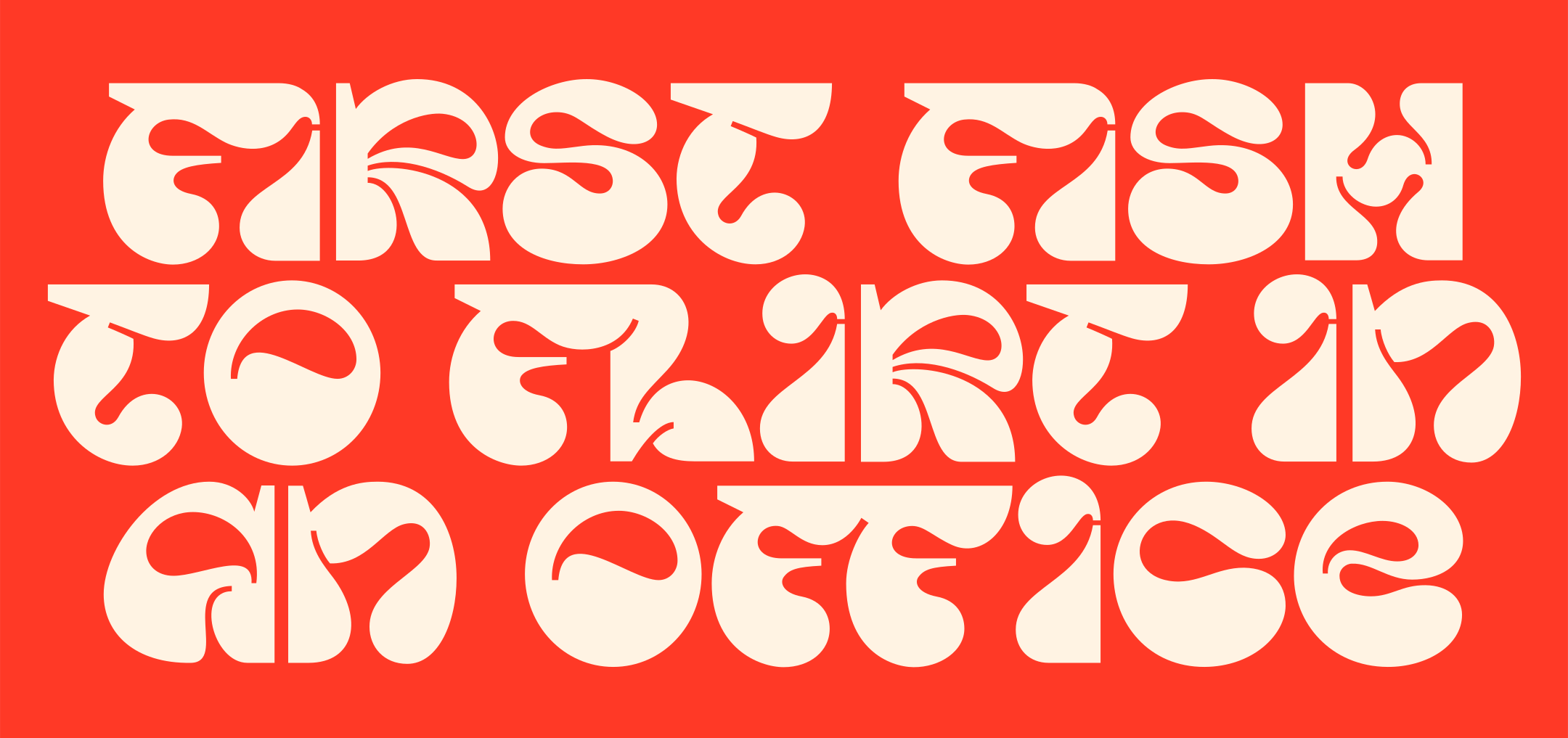
Arrogant Typeface Font
Description de Arrogant Typeface Font
Arrogant Typeface Font est une police d’affichage à casse unique qui se distingue par son expressivité et ses formes arrondies. La famille Arrogant se compose de trois graisses (normale, légère et grasse) et d’une police variable qui fonctionne bien dans plusieurs tailles et applications.
La police contient 310 glyphes, dont des lettres, des chiffres, des signes de ponctuation, des symboles et des ligatures, et prend en charge 93 langues.